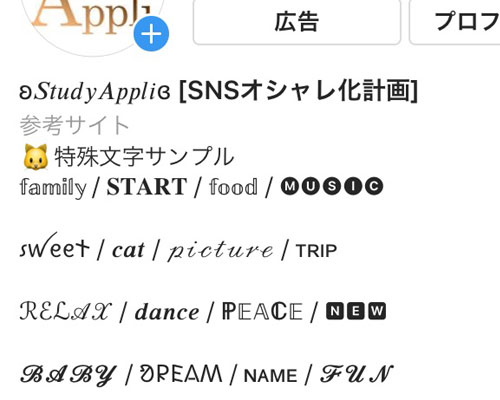
インスタで特殊文字を使う方法!特殊文字でプロフィールを可愛くしてみよう
インスタのプロフィールで珍しい文字やフォントを使っているのを見たことはありませんか?
私のインスタでも使っているのですが、以下のような文字です。
このような文字は『特殊文字』と言われていて、普段使用している文字のフォントとは違い印象も変わります。
インスタのプロフィールで特殊文字を使う方法がわからないという方も多いようなのでこのページで詳しく解説します。
インスタのプロフィールで特殊文字を使う方法
インスタのプロフィールで特殊文字を使う方法としては以下のステップが必要です。
1. 特殊文字をコピーする
2. プロフィールを編集する
iphoneやandroidなどを使っている場合、特殊文字をそのまま変換する事は基本的にできません。
一部であれば変換も可能ですが変換できる特殊文字の種類も限られているので、多くの方は特殊文字をコピーして利用しています。
特殊文字をコピーする
まずはインスタで使いたい特殊文字を探してコピーします。
インスタで使う特殊文字をコピーするには以下のツールを使います。
上記のツールを使って特殊文字を探してコピーしましょう。
ツールの使い方はカテゴリを選んでコピーしたい文字のボタンを押すだけなので簡単ですが、もしわからない場合には以下の記事を参考にすると良いですよ。
プロフィールを編集する
ツールを使って特殊文字をコピーしたらインスタを起動してプロフィール編集を行いましょう。
プロフィール編集画面では先ほどコピーした特殊文字をペースト(貼り付け)する事ができます。
特殊文字を貼り付けてプロフィール編集を完了させればその特殊文字がプロフィールとして表示されるようになります。
文字数が多かったり改行が多いとコピーした特殊文字を貼り付けできないケースもあるので注意しましょう。
インスタで特殊文字を使うとこんなに変わる
特殊文字を使ったプロフィールと通常のプロフィールとでは見た人の印象も全然違います。
例えば、
• music
• fashion
• color
といった文字なども特殊文字を使うとこんな見た目に変わります。
・?????
・???????
• ᴄᴏʟᴏʀ
特に英語の文字などは特殊文字にする事で斜体や筆記体などが使えるのが良いですね。
また、アルファベットの大文字を小さくした文字も人気です。
こういう文字を工夫して使っていけば可愛くて目立つプロフィールが作れるようになります。